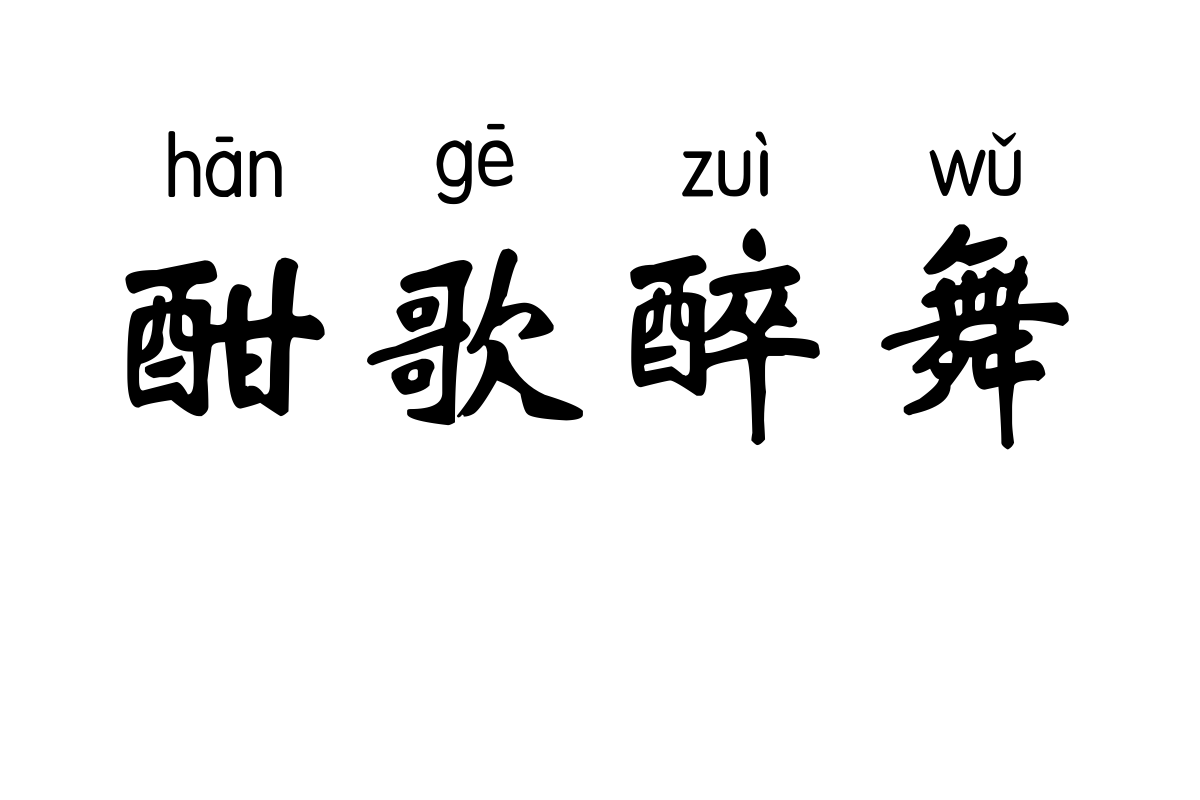
斑马新魏碑拼音体是一种独特的字体设计,它结合了传统书法和现代设计理念。这种字体以其独特的笔画结构和流畅的线条而闻名,给人一种优雅而有力的感觉。
斑马新魏碑拼音体的主要特点是它的笔画粗细变化明显,线条流畅自然。每个字的笔画都经过精心设计,使得整体看起来既有力度又不失美感。此外,这种字体还采用了一些特殊的装饰元素,如波浪线、曲线等,增加了字体的艺术感。
斑马新魏碑拼音体的应用场景非常广泛,包括广告、海报、书籍封面等。它的设计独特,能够吸引人们的注意力,同时也能够传达出一种文化的气息。
总的来说,斑马新魏碑拼音体是一种非常有趣且具有艺术感的字体,它能够为各种设计项目带来独特的视觉效果。